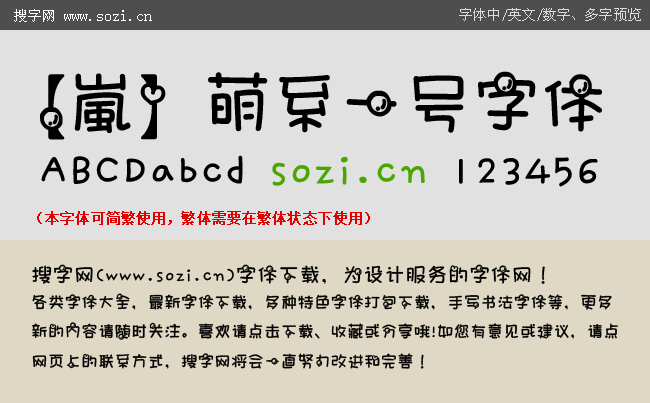
萌系一號(hào)字體
搜字網(wǎng)給大家提供一款萌系一號(hào)字體手機(jī)中文字體下載。這款手機(jī)字體是一款POP風(fēng)格的卡通字體,字體上還嵌入了可愛(ài)的卡通圖案,是非?蓯(ài)的一款字體,特別適合喜歡手機(jī)字體個(gè)性一些的朋友在手機(jī)上安裝使用。